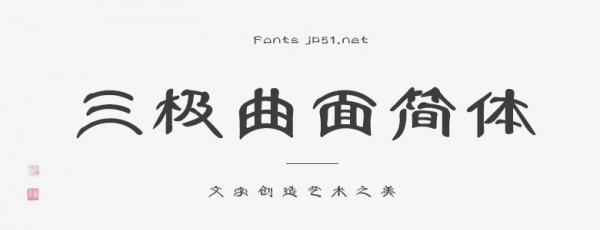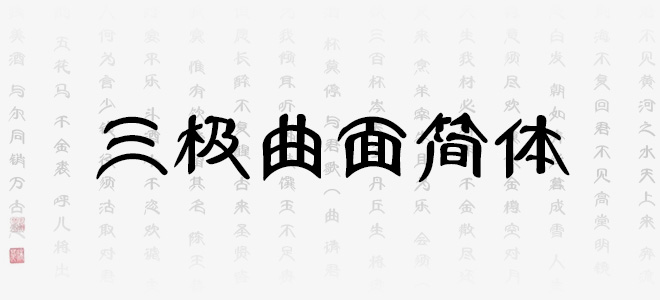
三極曲面簡體是一款裝飾意味濃厚的創(chuàng)意字體。這款字強(qiáng)化了筆畫中大部分的弧線,筆畫的中部向上統(tǒng)一做了圓弧拱狀處理,筆畫圓潤,橫、豎交叉感強(qiáng),特點(diǎn)明顯。大膽創(chuàng)意,字形穩(wěn)定堅(jiān)實(shí),又不失文字的識別性。適用于廣告、產(chǎn)品包裝設(shè)計(jì)應(yīng)用。
三極曲面簡體